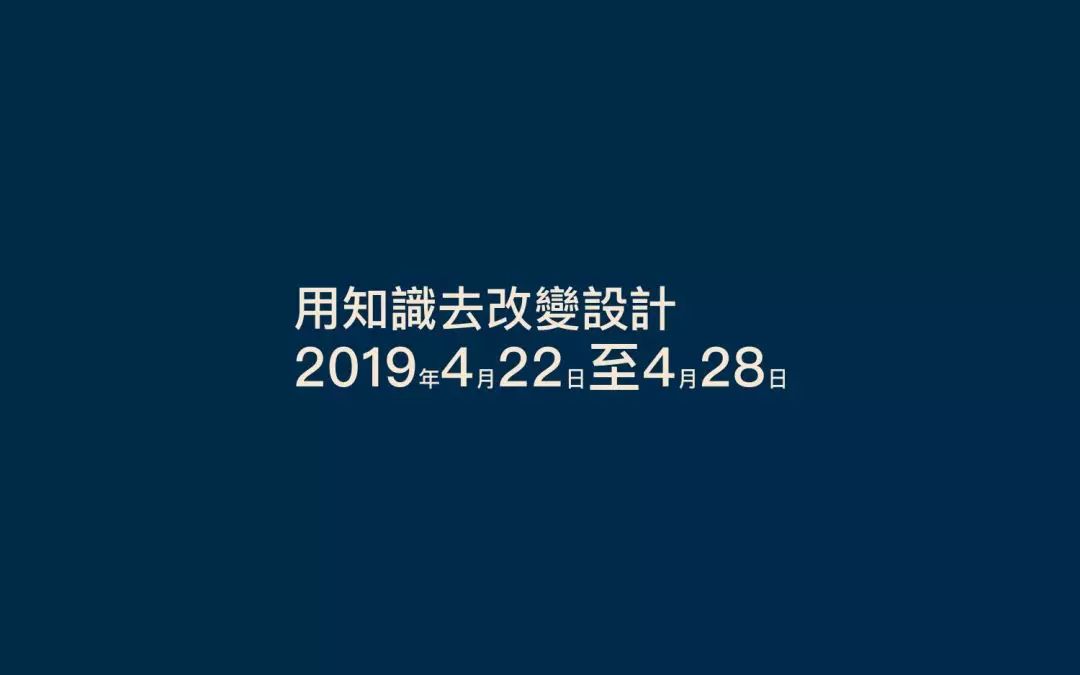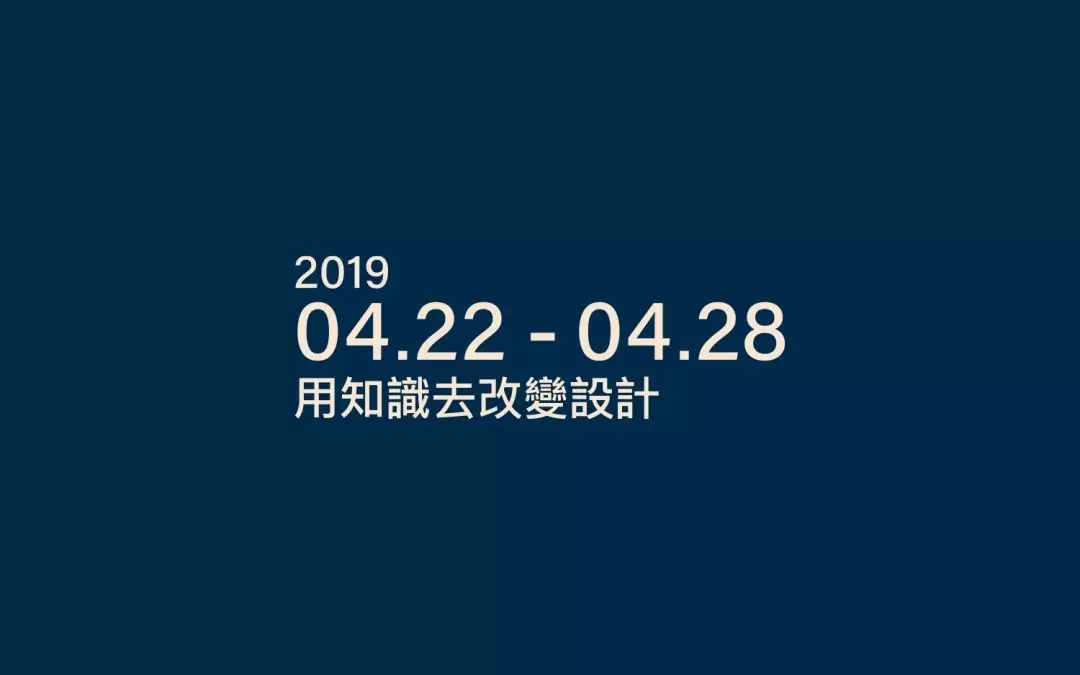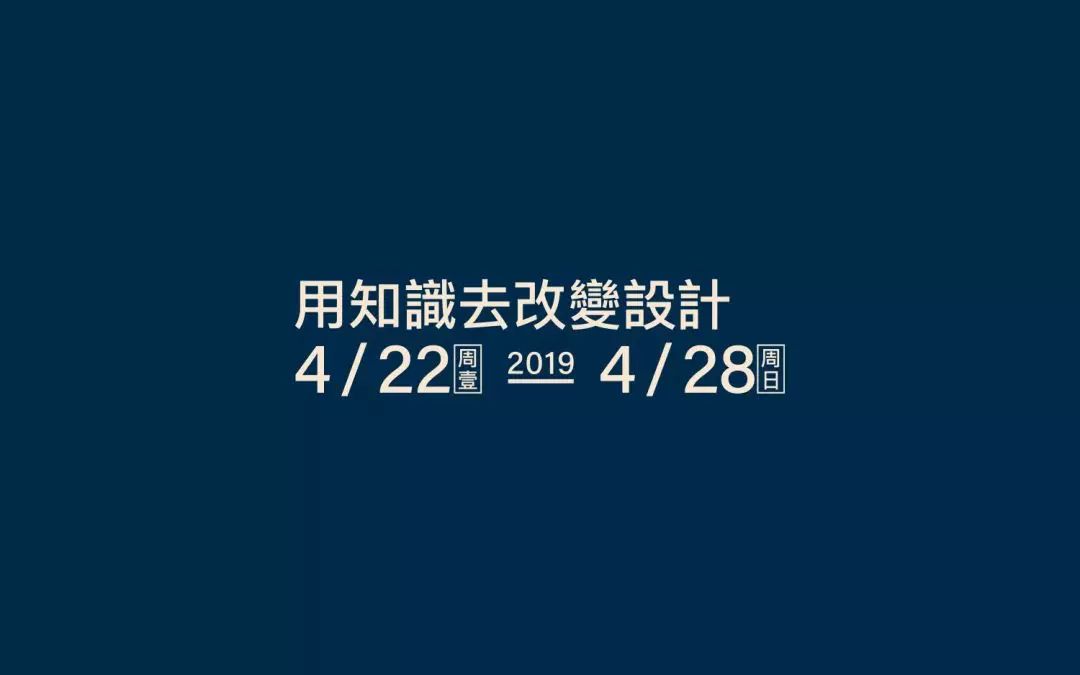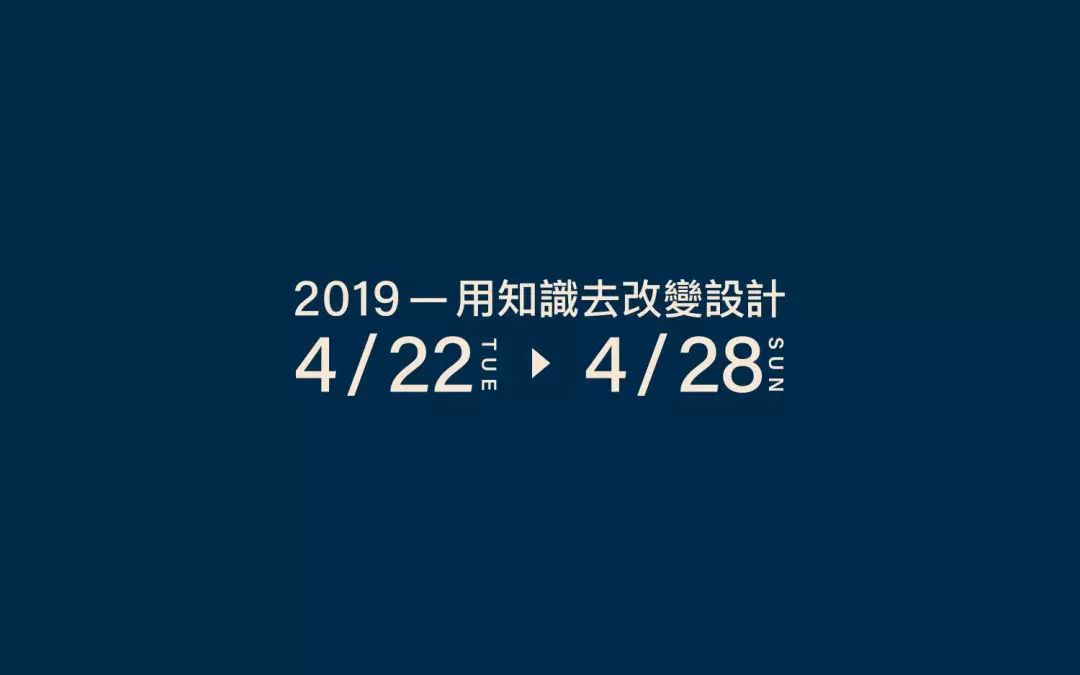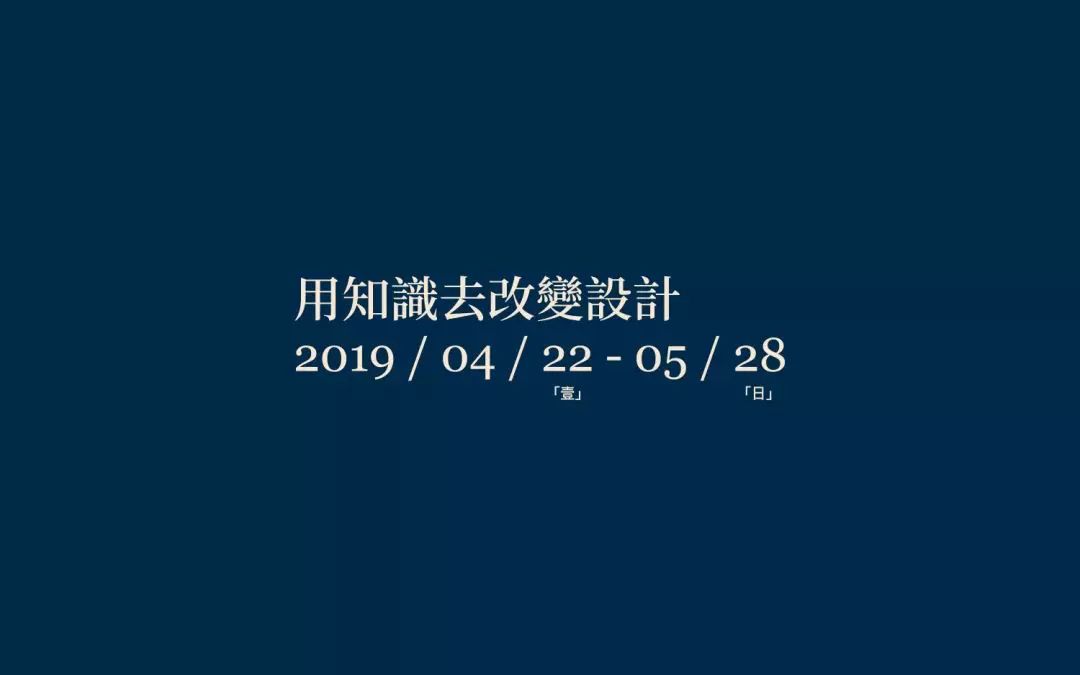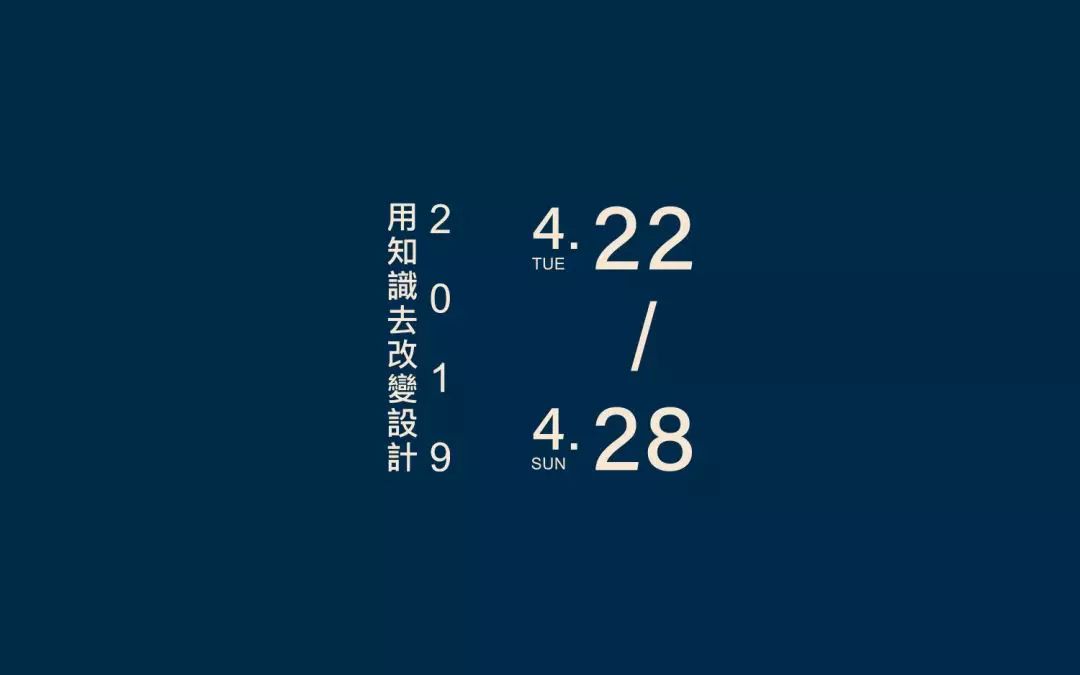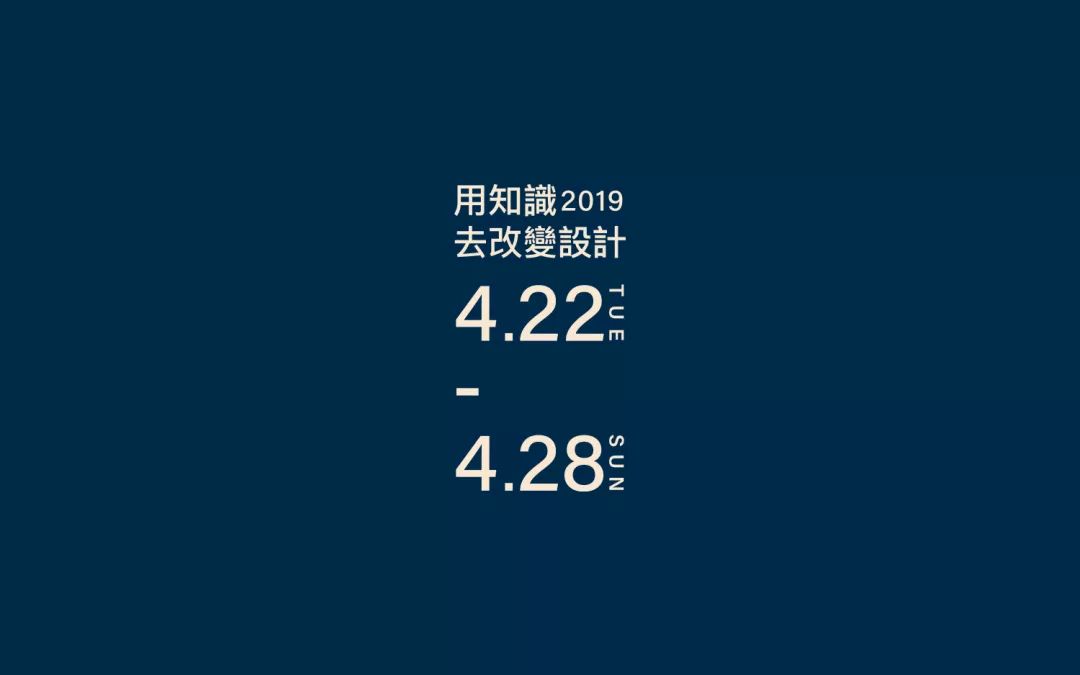
海报当中的日期,可能不如主标题那么显眼,但也不能忽视,除标题外的一些小信息同理,一个小细节的美观同样会影响整个版面的设计。
你是否还是拿到设计文案不分析?不思考?直接复制黏贴就往画面放呢?下面用实际例子来讲解一下,海报中日期编排的多种可能性。
信息编排,并不是将文案直接复制粘贴就可以了,在这里,设计师需要对信息进行刻画,在易于阅读与识别的同时还要具有观赏性,让受众愿意去阅读并且记住它。话不多说,我们直接来看,一个简单的信息编排的多种可能性。
以下面一段文字为例,下方编排是最为平常的一段文字,但怎么把这段文字编排的具有设计感,同时也利于阅读,则需要设计师去对他进行美化。
· 01 ·
采用编排中的左对齐方式(右对其同理)进行编排是较为平常的编排方式。将“年月日”字眼信息缩小,采用大小对比增强信息之间的跳跃率,在视觉上让版面更加活泼。
· 02 ·
采用编排中的左对齐方式(右对其同理),弱化不太重要的信息。在这将年份与小标题缩小,突出日期,增强版面的对比时重点。将月份信息换成“·”和加入连接线,让画面更加简约和利于阅读。
· 03 ·
和上方一样,将月份字眼替换成符号“/”,同时注明是周几,这样能让阅读者更清晰的知道时间的具体信息。将年份信息放在连接线上,让年份和连接线一样起到连接的作用,同时还能引起阅读者的注意。
· 04 ·
把周几的信息替换成英文,将“至”换成符号►进行体现,在我们阅读的时候会自然的从左至右进行阅读,将信息这样处理还可以丰富信息编排的细节感。
· 05 ·
选取具有跳跃感的字体,让画面更具韵律感,还可以把周几信息编排在日期下方当中,明确具体时间,同时让版面层次更加丰富。
· 06 ·
去除年份,除非特定活动一定需要年份,除外的话可以删减年份,突出具体时间,将日期和具体周几进行突出,周一至周日连接处采用“横线”进行连接,除小编题外两端对齐,让版面看起来更加饱满。
· 07 ·
将小标题突出,分成两行,下方放置日期,若版面右上方感觉空洞,可以缩小年份放置此处。
· 08 ·
将信息在视觉上处理成大概一样的字重,小标题分成两行进行编排后放置年份下方,日期信息可以竖排进行摆放,添加倒三角符号指引读者从上至下阅读。
· 09 ·
同样是竖向阅读,可以弱化小标题和年份,突出日期;为了增加画面的层次,将月份稍稍缩小,放大日期,日期采用上下编排方式,并用“/”符号放至中间进行区隔,指引读者从上至下阅读。
-总结 -
文字编排是为了让读者更好的进行阅读和享受阅读过程,编排方式远不止这简单的几种,方法只是开阔我们的思维,灵活运用所学的知识才是最重要的。